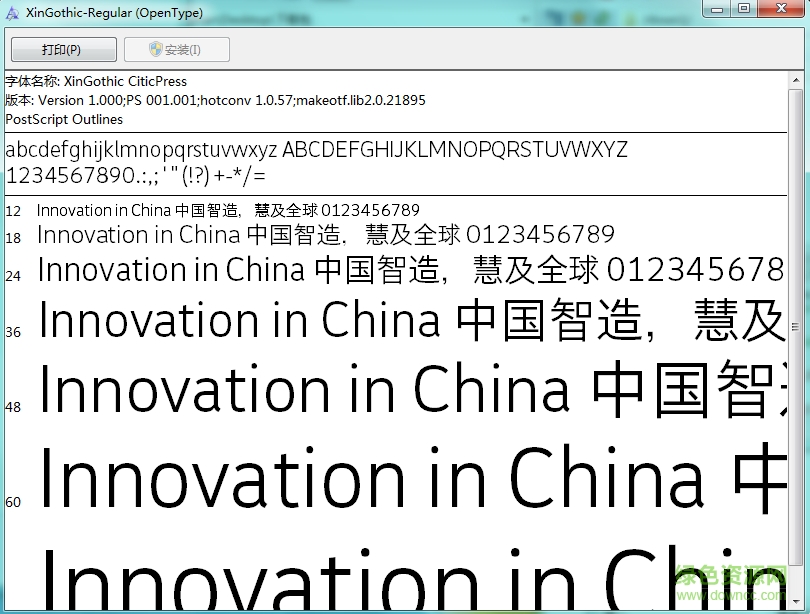
信黑體是一款匠心獨(dú)運(yùn)的中文字體,簡單大方的造型和端正秀氣的外觀,給你很正式的文字視覺體驗(yàn),讓人閱讀起來更顯舒適,來綠色資源網(wǎng)即可免費(fèi)下載本系列字體哦!
呈現(xiàn)給您的信黑體,絕不只是字型,代表了濃縮30年造字純釀,Sammy將他畢生心血,以一筆一畫的精刻,描繪出不慍不火、簡潔俐煉的筆劃氣韻,每個字力求布局均衡,極像是儒家描述的中庸境界,就請您細(xì)細(xì)品嘗。
信黑體的筆劃表現(xiàn)出現(xiàn)代俐落簡潔的風(fēng)格,迥異于十年前設(shè)計的黑體字型,在尾部采取俐落的切線呈現(xiàn),筆劃具備傳統(tǒng)書法的力道,整體視覺呈現(xiàn)出最適閱讀的一致協(xié)調(diào)風(fēng)格。
信黑體是專為電子屏幕而設(shè)計的中文字體,每個weight都經(jīng)過不斷重復(fù)的螢?zāi)徽{(diào)校,來取得最佳的視覺平衡和效果,尤其適合高品質(zhì)視網(wǎng)膜螢?zāi)弧?/p>